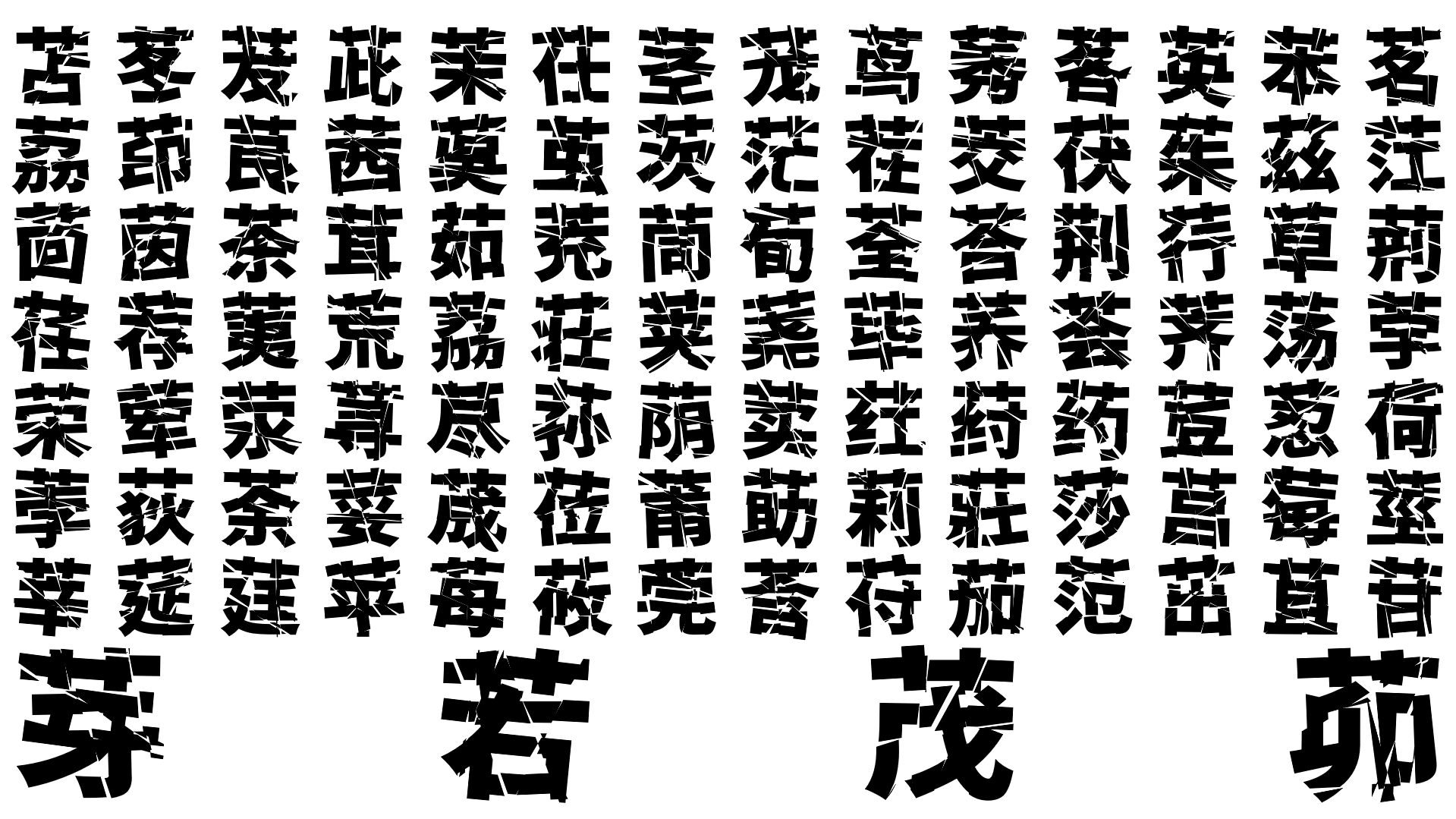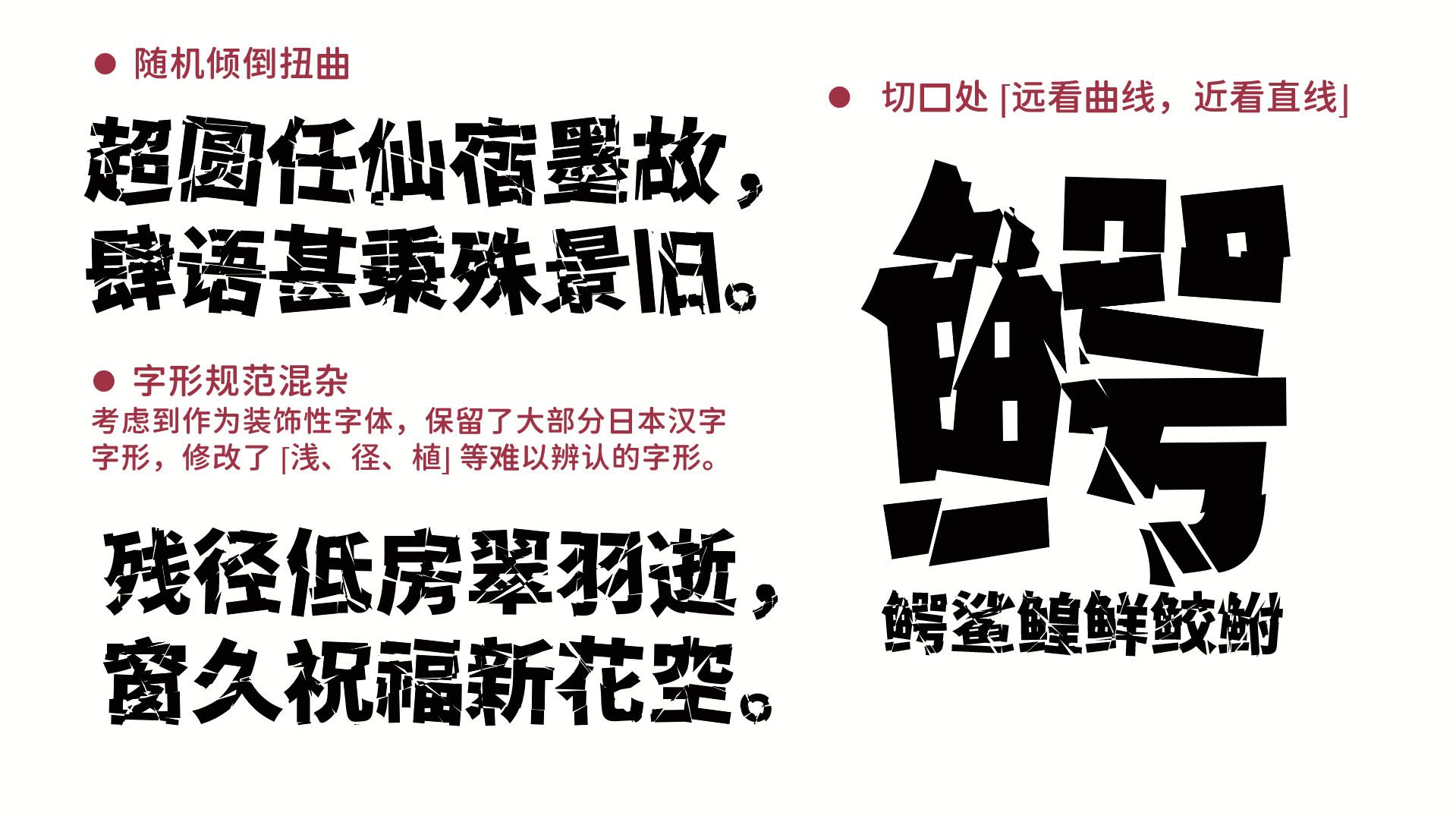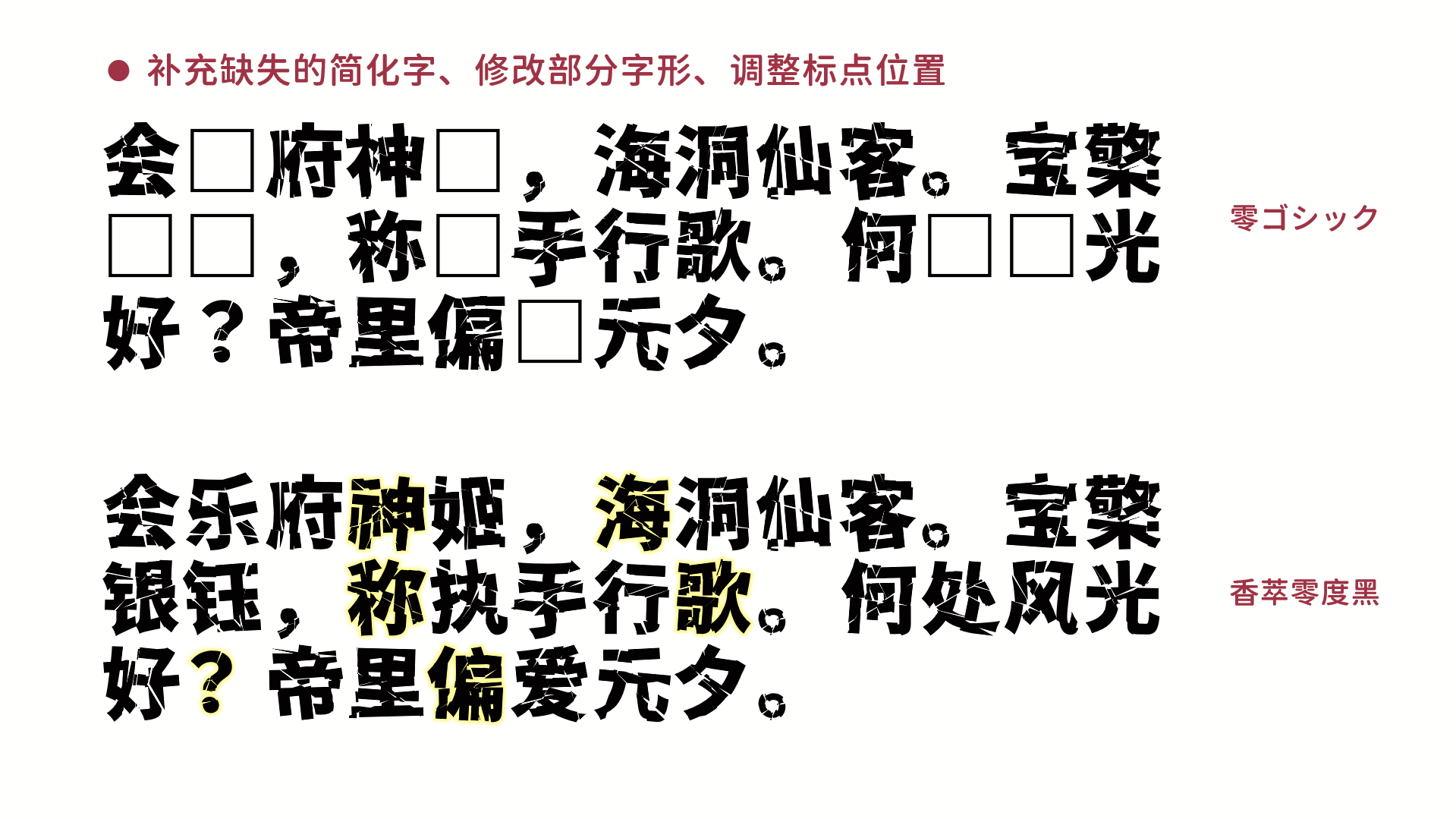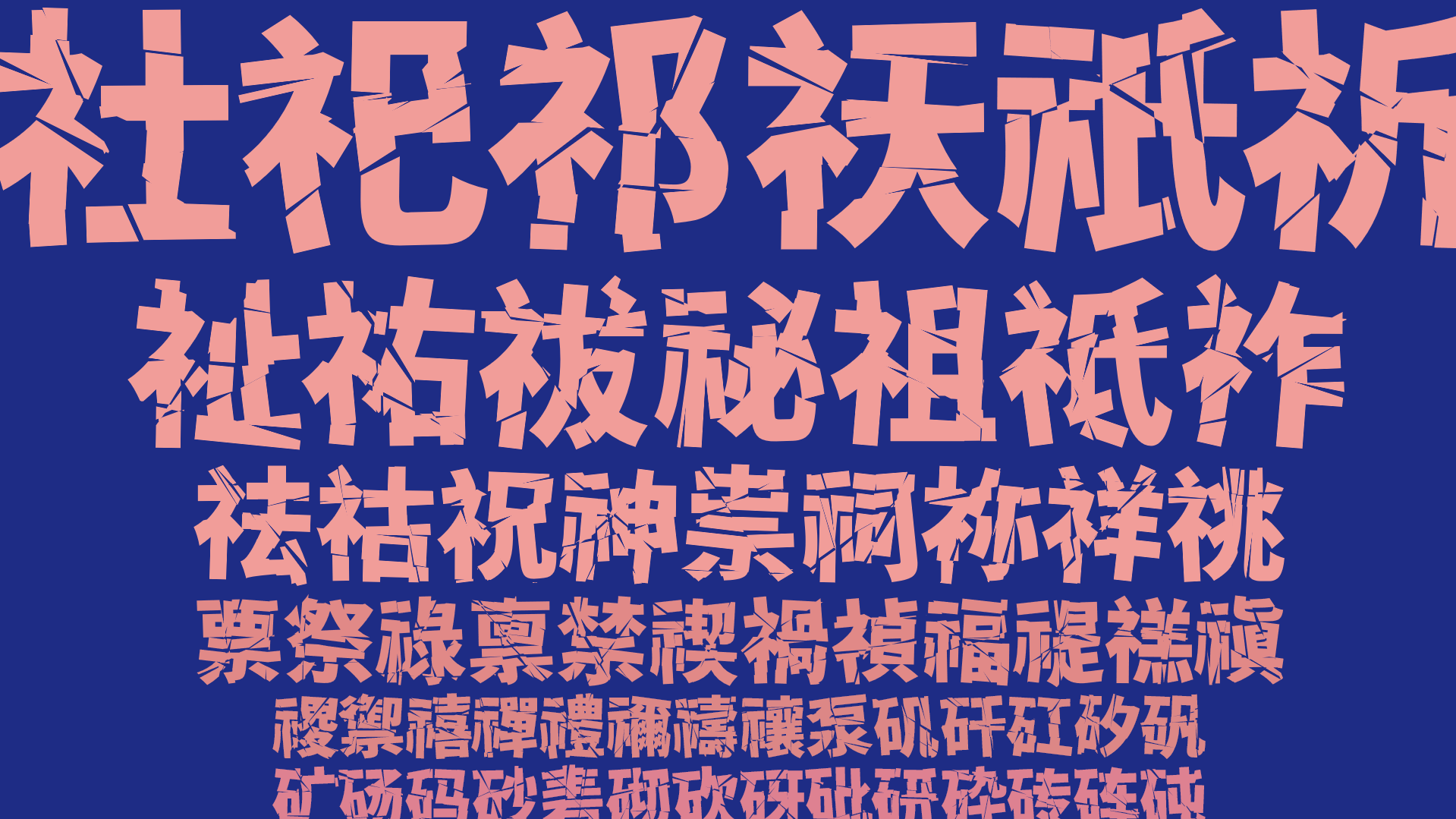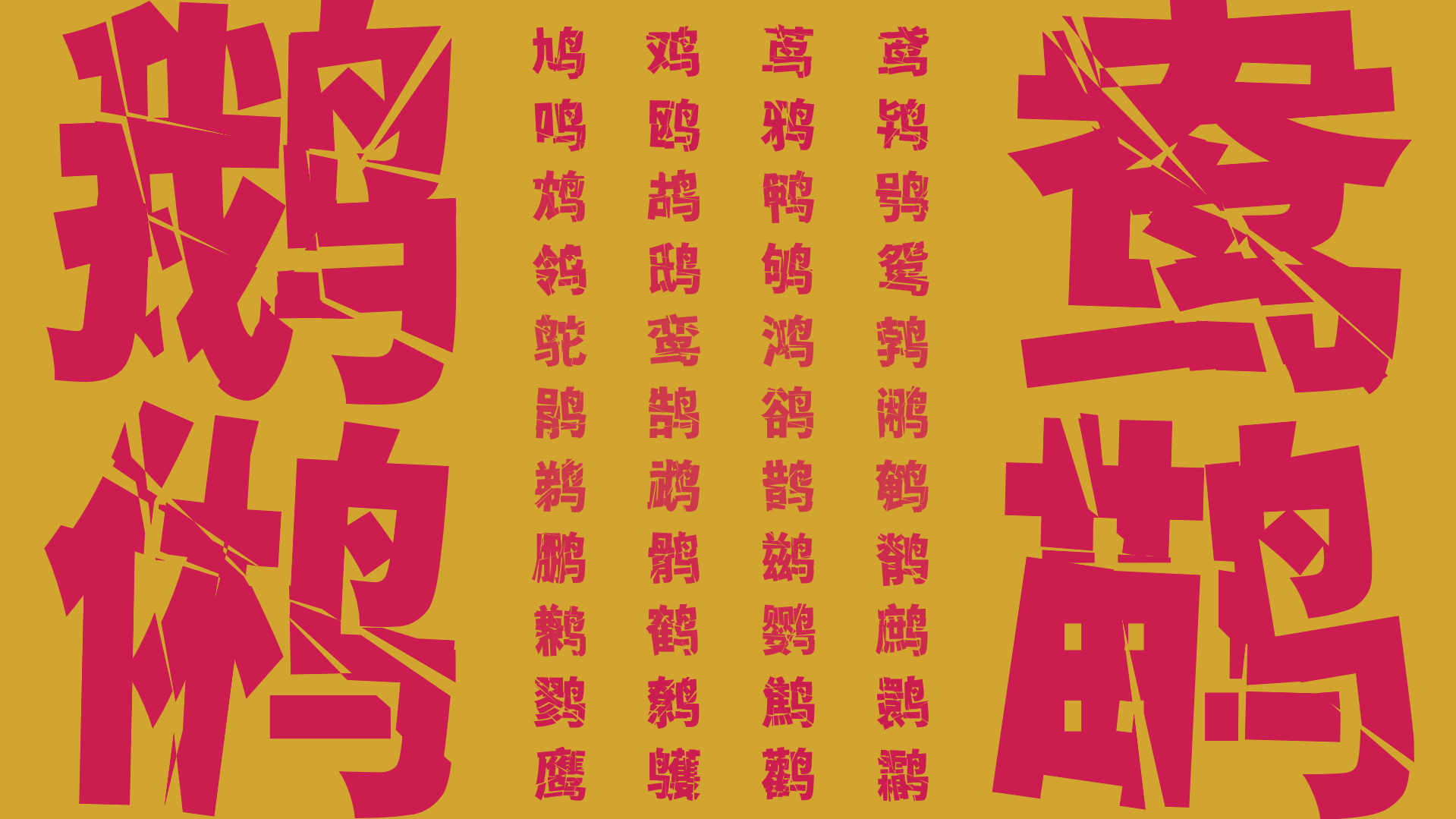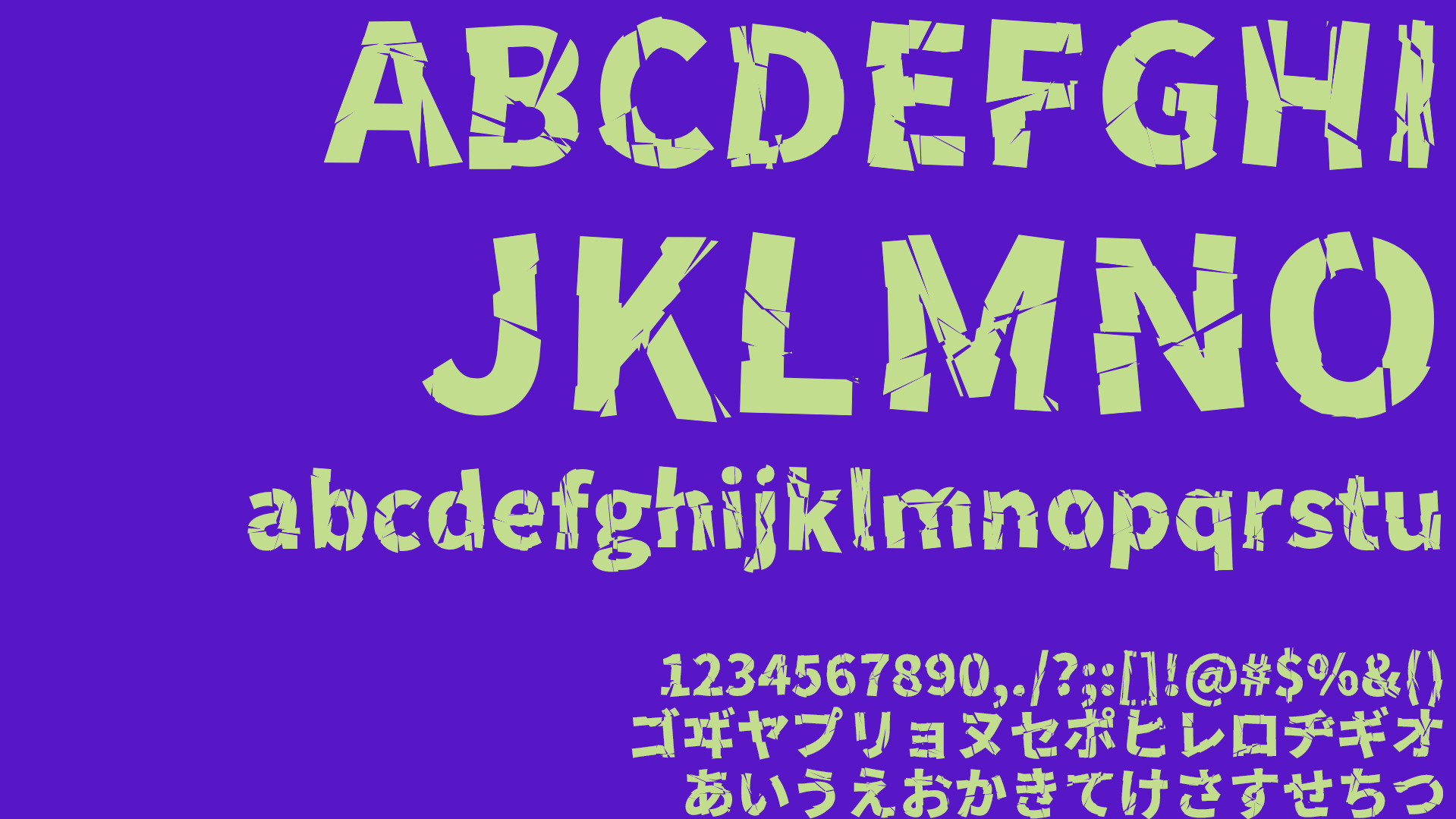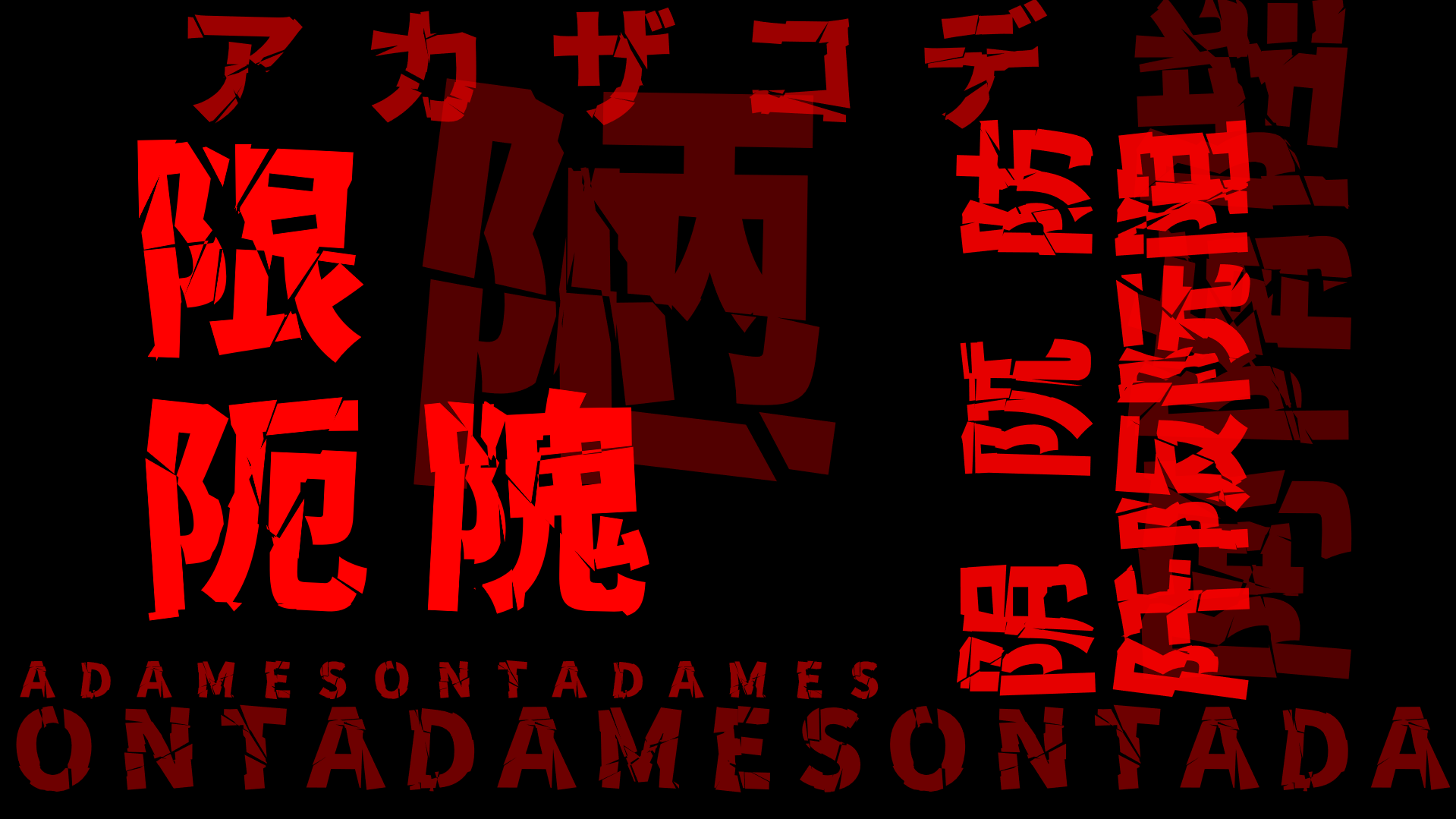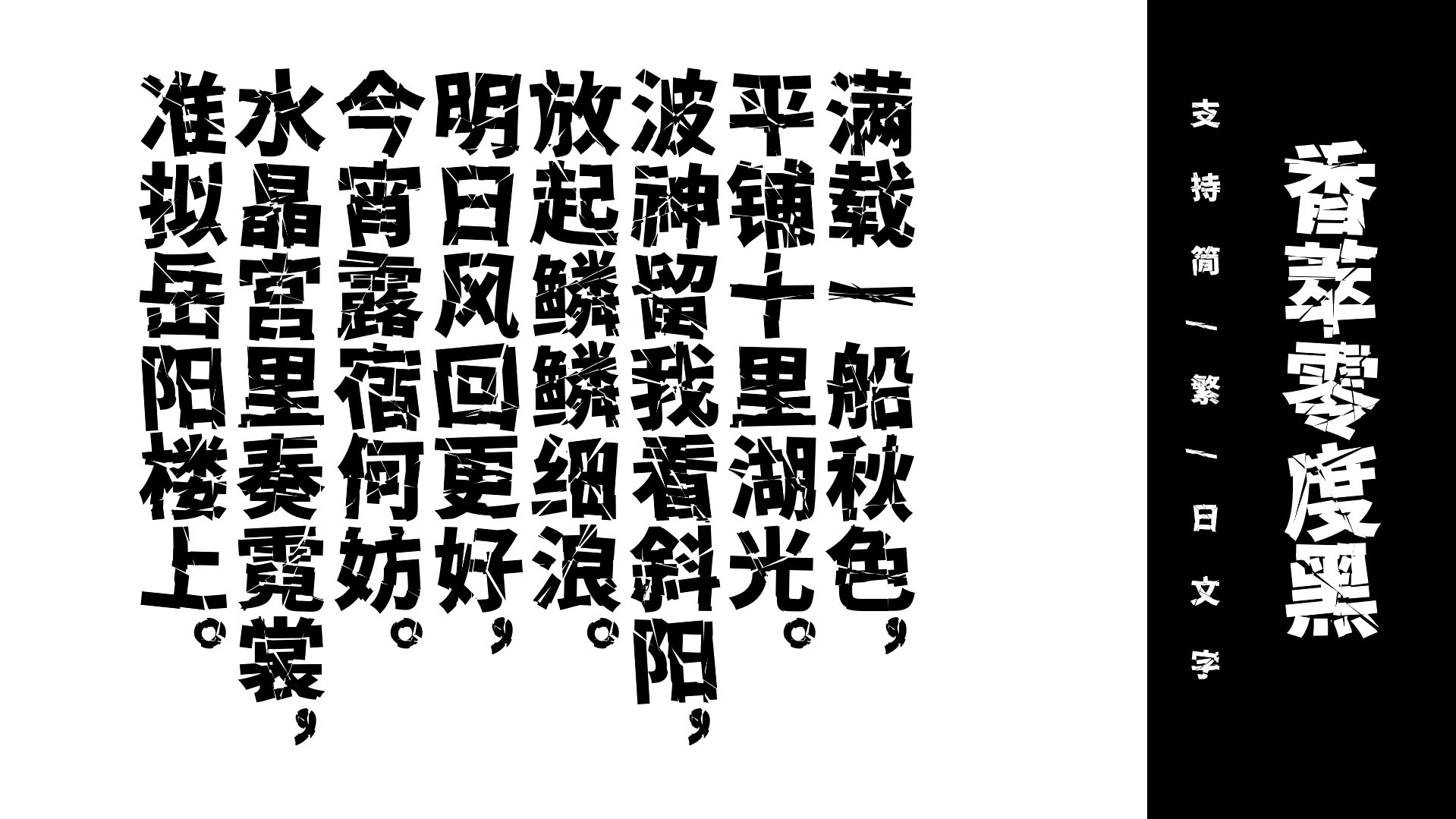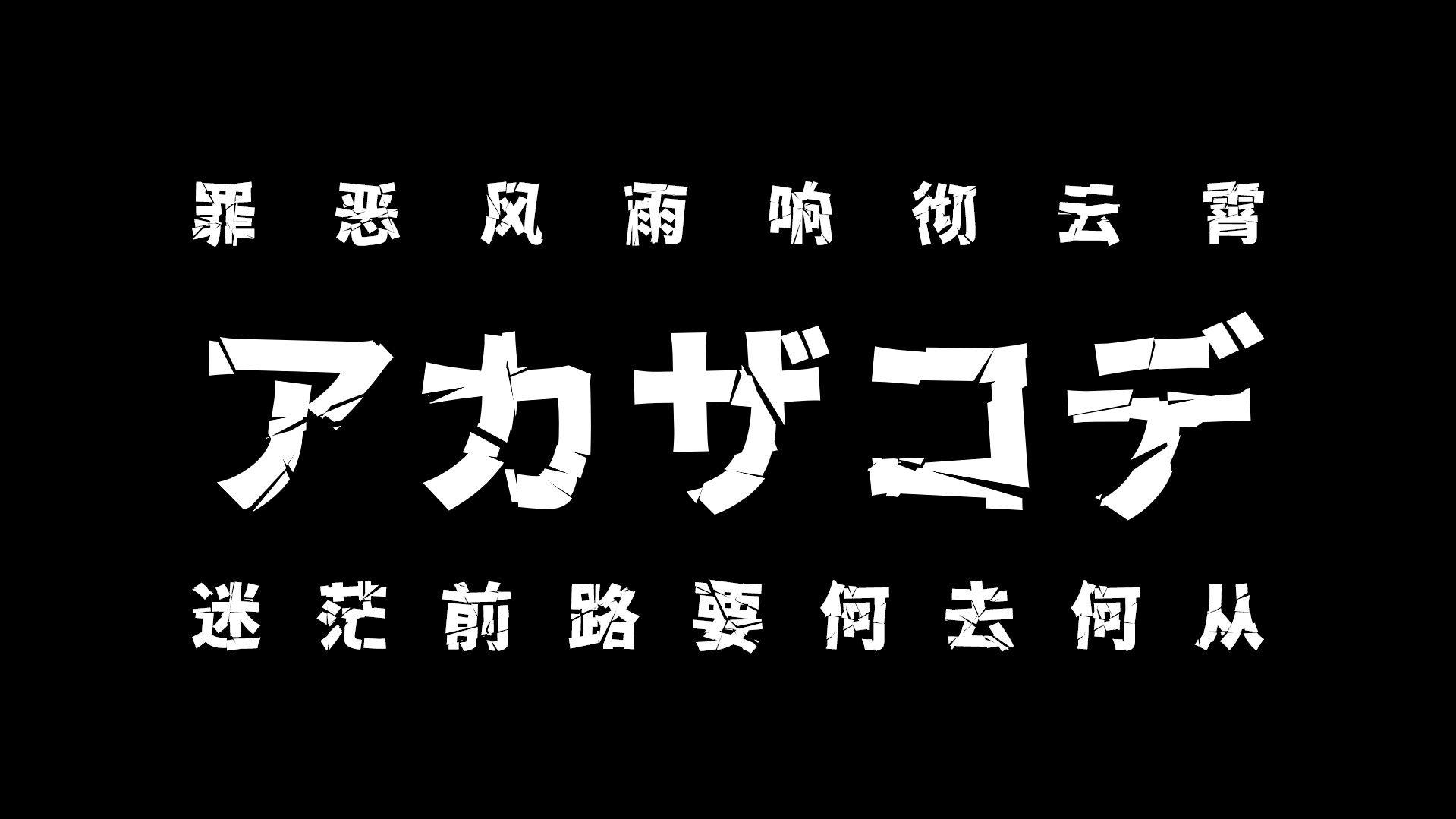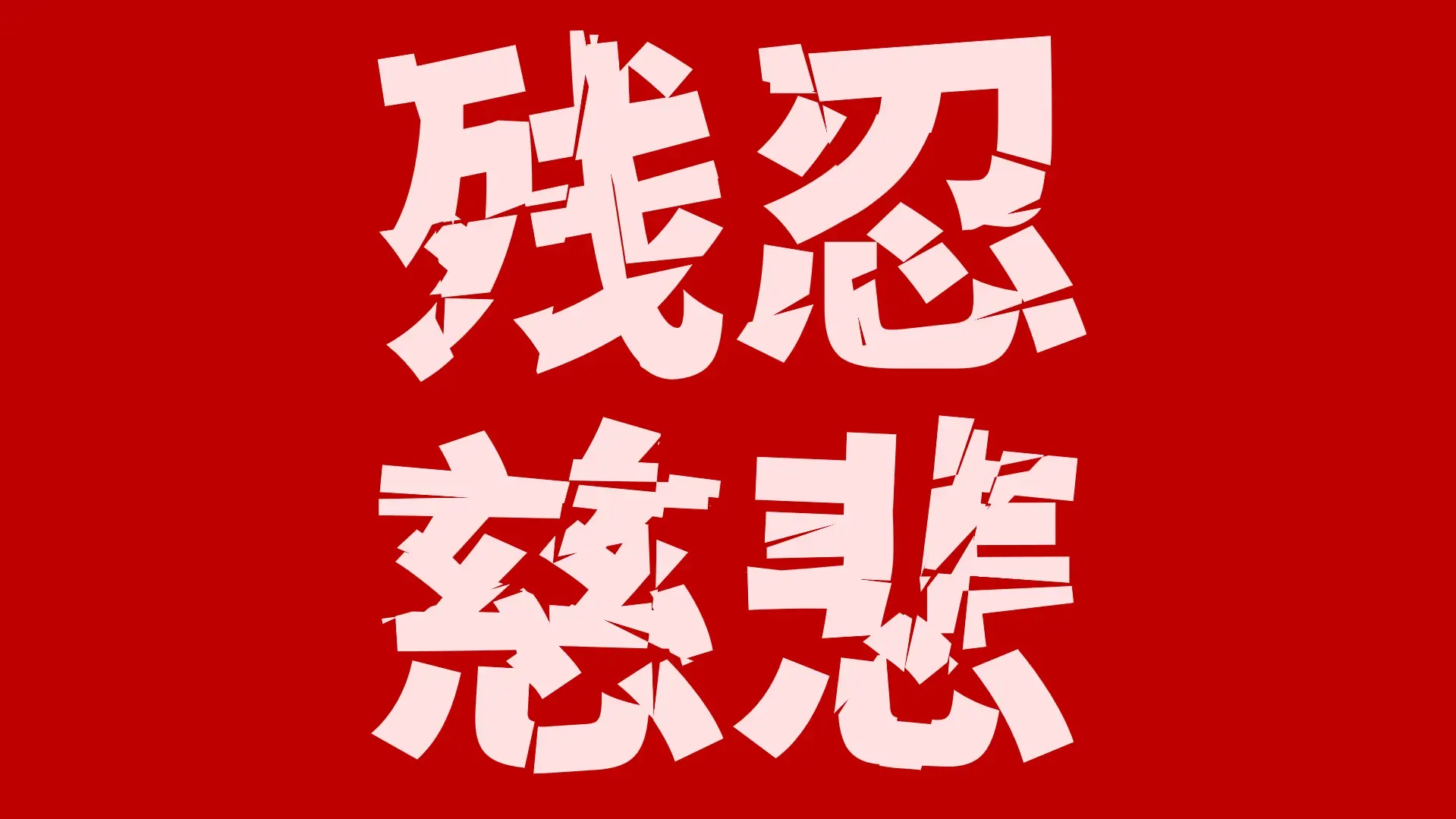
香萃零度黑是日文字体【零ゴシック】的简化字补齐版本。字体具有强冲击性,个性较浓,切割与扭曲明显。本字体属于开源项目,允许全社会免费使用。
在字体的笔画上做了扭曲、分裂的设计,在切口处呈现远看曲线、近看直线的效果。考虑到作为装饰性字体,(在不影响辨识的情况下)部分日本汉字字形仍然保留。根据简体中文书写习惯,微调了标点的位置。
破碎的字体像冰面纹理。源字体名零ゴシック,ゴシック即gothic,意为黑体字,香萃零度黑由此得名。
1.修复了竖排文字字距不均的问题;
2.为了美观,重新制作了以下209字
【东击凿凭伤你侦侨倩前劂叁厣匮匾尨渲泻汇满溉涟濉潞澧涑岁咕呸唤吗呃吧呢圊囝囡尘垒垫圳垛媳姗带衔废晚晦户桥柠楗椐柽摁摆摇搞抻搛搠摈搌挢整现望烘烬焕炕炖炜炼焊焗烯热煞犟獐猸猱猡牖秆稃祸祧祯穹矬盯睽真着痨痦瘅畹疃结线续绳绒缢绔綦褴褰筘虑虏荡萃蓦茔荨芨芎芑翘翩糈胁腾蜮罢该说谲郾邾郦鄞鄣鄢账费览觎输较跃趼这过迈逊递遥违遛迤赵趔趑酗酮酯酐酤酡酾醮觫觳觥阳险陡难钱钥锈锌长阗阙闱香饭饿马骁鸟鹅鸯鸸鹁鹇鹕鸺鹛鸫鸬鹂鱿鲈鳘鲐鳓鲎麂黾齐龟】;
3.增加了以下95个字符
【砟碥叆叇嬿玙玥珅珺琍琤瑀瑄璿鸰鹟鹡鹴鹮赑赟觍坶垸埝埤堞塄墉攉掱枧柃枨枰枵柙栝栳楦榀槔槠樘樨橛檑檩檫橥燊毹氆氇炆爝耔耠耢耥耪蓠萹芄菑鼢鼯龀颙闿镚覅朆觯朐螣肏窅甪毐惢弶屌屄囷囧吔啫嘚嘢嘫嘅嗮嗐唝】;
4.调整了中文冒号和分号的位置。